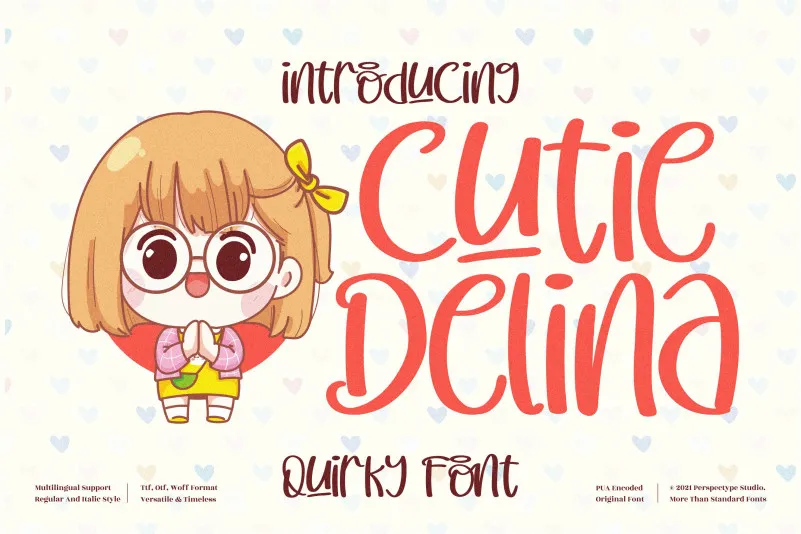
A Cutie Delina Font é uma seleção única e divertida de tipografia para uso em criatividades diversas. Perfeita para momentos especiais e criações infantis, como festas de aniversário de bebês ou batismos, além de ser ideal para títulos de livros infantojuvenis com um toque delicado e alegre. Esta fonte display é perfeitamente adequada a qualquer design que exija uma delicadeza e um tom alegre, tornando-a uma escolha ótima para quem busca personalizar seus trabalhos de forma única e encantadora. Sua versatilidade faz dela uma fonte ideal tanto para designers gráficos quanto para criadores de conteúdo infantil.